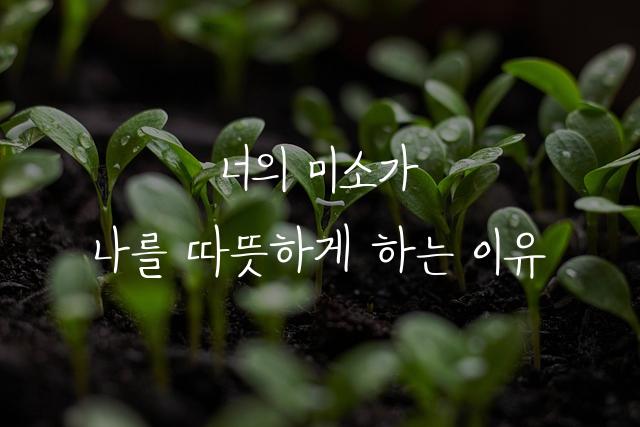
한둥근바탕
한둥근바탕은 윤디자인에서 제작한 바탕체로서, 책과 같은 인쇄 매체에 최적화되어 있습니다. 부드러운 곡선과 둥근 모서리가 특징인 이 서체는 따뜻한 감성을 전달합니다.
윤디자인
2가지 굵기
한국어, 영어, 일본어, 특수문자 지원
친근하고 부드러우며 편안한 느낌을 주는 목소리
한둥근바탕은(는) 바탕 스타일 계열의 생김새를 가지고 있으며
웹/앱 디자인, 프레젠테이션, 보고서/문서 등에서 자주 활용되며, 효과적인 메시지 전달에 적합합니다.
이 폰트는 교육, 출판/미디어, 라이프스타일 분야에 잘 어울리며,
친근한, 편안한, 단순한 느낌을 담고 있는 것이 특징입니다.